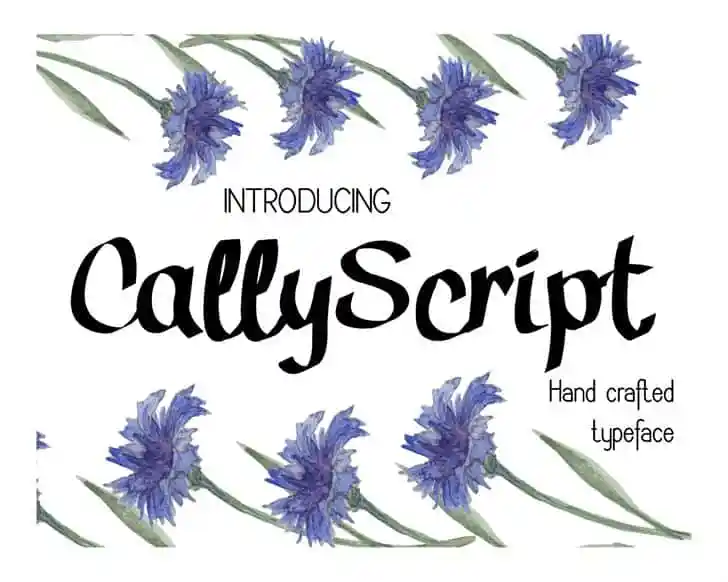
Cally Font – Fonte Grátis
Cally Font
A Cally Font é uma elegante serifada ideal para desenhos artísticos e design personalizado. Inspirada nas técnicas tradicionais de canetado, esta tipografia digital oferece um ar despojado que combina perfeitamente com trabalhos criativos. Se você está procurando por uma fonte que não apenas se destaca no seu projeto mas também permite uma sensação artística e original, a Cally é definitivamente para você. Com uma utilização gratuita pessoal, bem como opções de licenciamento comercial disponíveis online, o acesso à esta font seria um verdadeiro tesouro para qualquer designer ou amante da arte. Além disso, sua simplicidade permite que se adapte facilmente aos vários estilos e formatos do seu design, tornando-a uma escolha versátil para projetos variados. Se você está procurando por algo que brilhe em um projeto de escrita formal ou personalizado, a Cally Font pode ser exatamente o que você precisa.